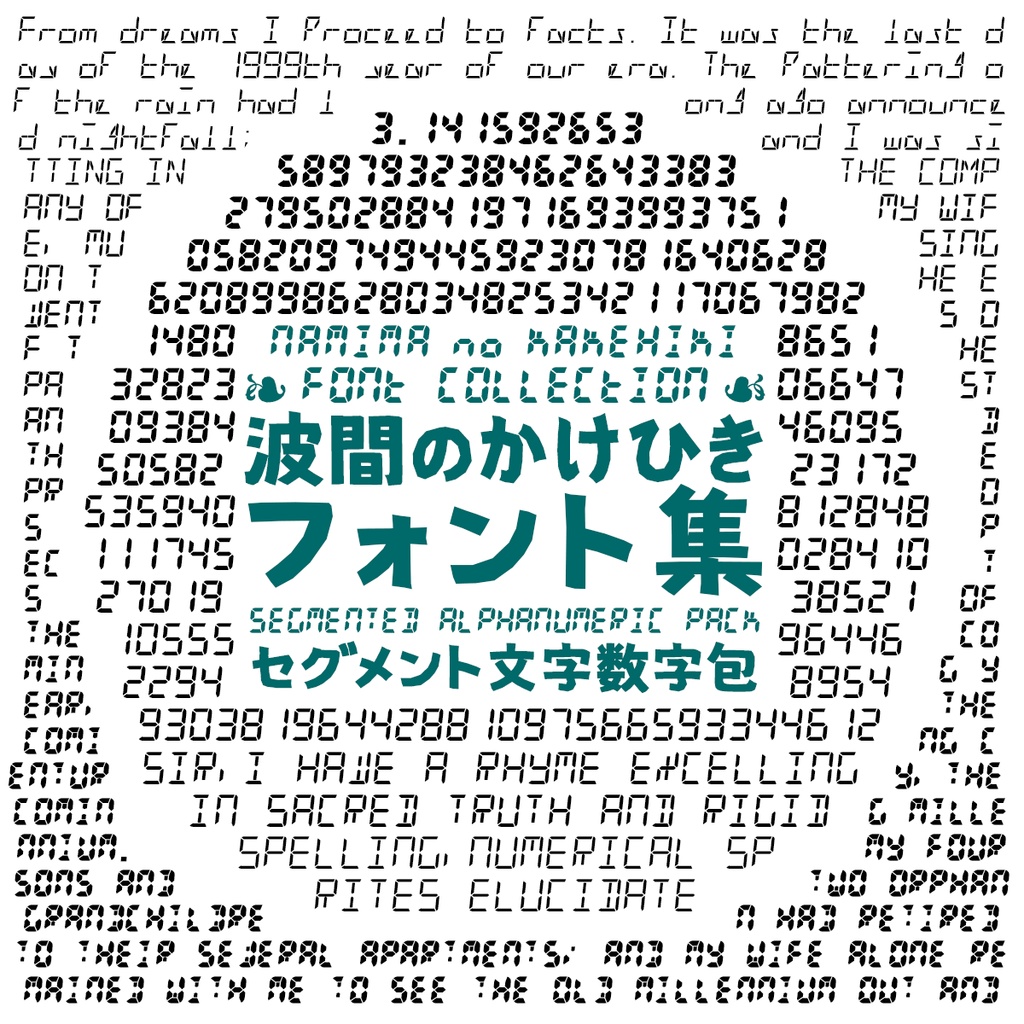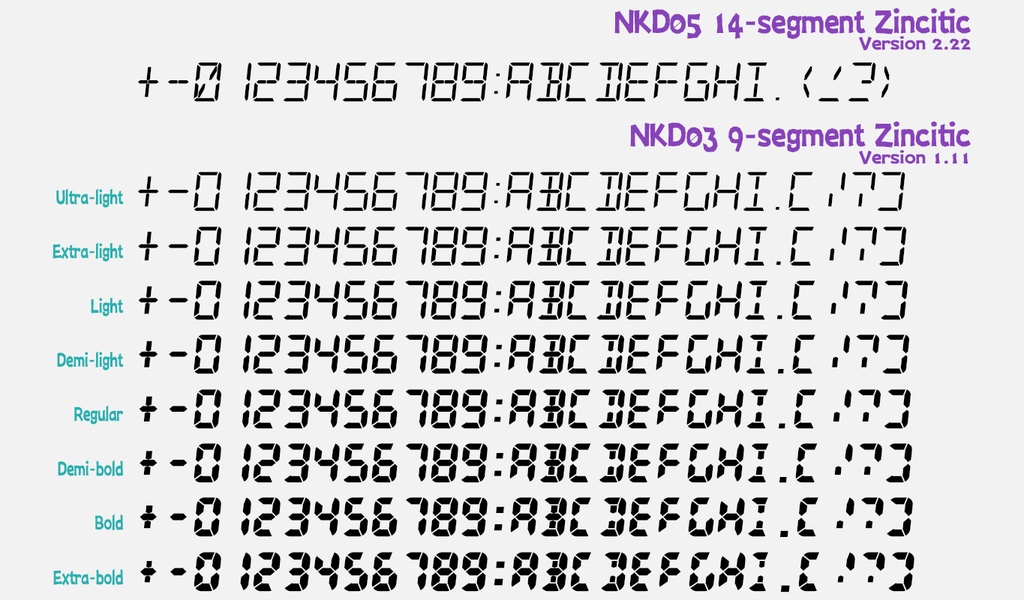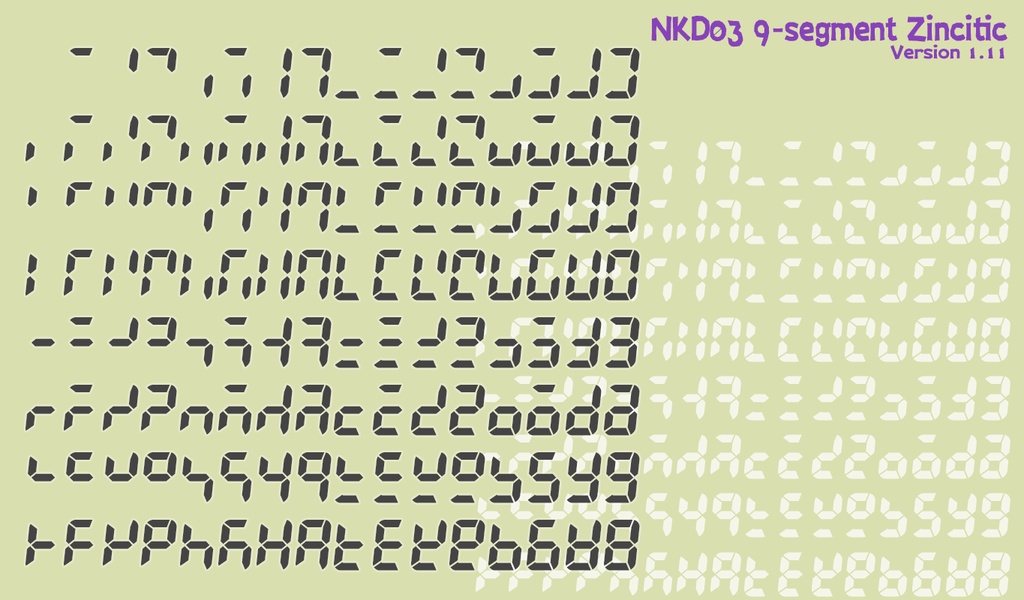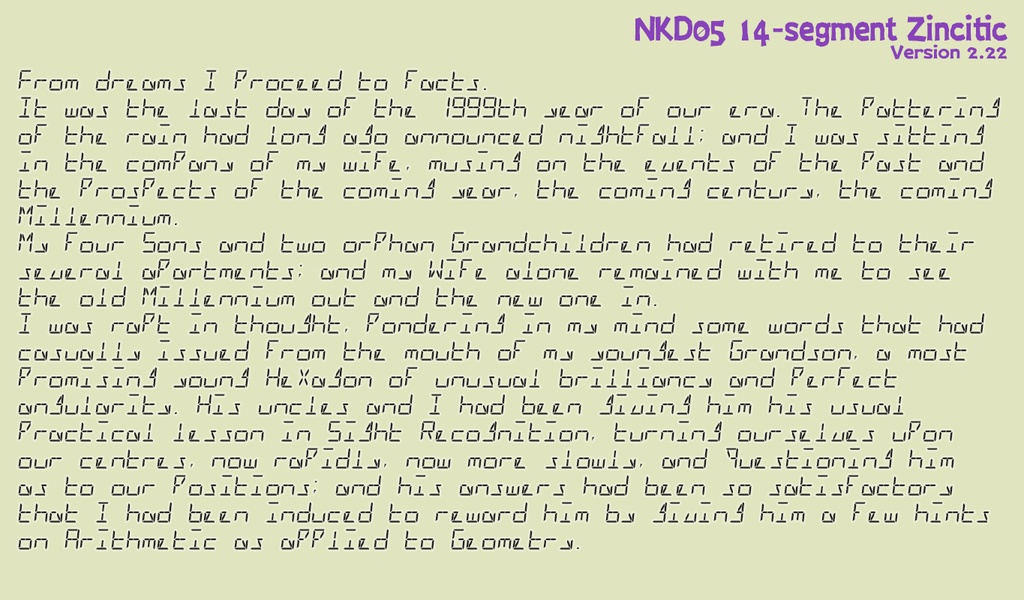
波間のかけひきフォント集・セグメント文字数字包
NAMIMA NO KAKEHIKI FONT COLLECTION - SEGMENTED ALPHANUMERIC PACK 🔤 独自デザインの9セグメントディスプレイ、および14セグメントディスプレイの数字や文字のフォントです。 (過去にフォント集CDに収録して頒布したものから大きく更新しています) 9セグメントのフォントは細字から太字まで8種のウェイトを用意し、数字や基本的なラテンアルファベットすなわちASCIIの範囲の文字を収録しています。 14セグメントはウェイトは1種類で、数字やラテン文字に加えて基本的なギリシア文字やキリル文字、雑多な記号などにも対応しています。 いずれも、0から9の数字についてはごく一般的な 7セグメントのフォントとして使用できます。 また、7セグメントで表示しうる128とおりのパターンも私用領域にすべて収録しています。 ❖ 当フォント群の一般的な目的での使用 (文書や画像の作成、装飾としての利用など) は私用、同人、商用を問わずご自由にどうぞ。 ✽ 形式: フォントはTrueType、添付資料はPDF
収録フォント群
❖「9セグメント Zincitic」 NKD03 9-segment Zincitic • Ultra-light • Extra-light • Light • Demi-light • Regular • Demi-bold • Bold • Extra-bold ❖「14セグメント Zincitic」 NKD05 14-segment Zincitic